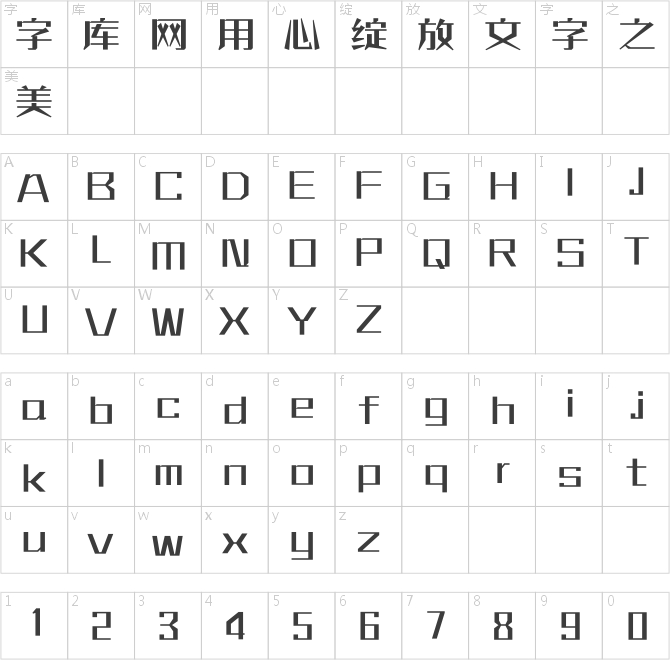
方正新恒刀刃體 詳情頁
方正新恒刀刃體字體下載
方正新恒刀刃體是在老式板報類字體的基礎(chǔ)上進行改良規(guī)范的,該字體所有筆畫全部以直線表現(xiàn),撇、捺、點、勾收尾處均采用切角處理,似刀頭、似利刃,故取名刀刃體,是一款既有力量感,又有活躍感,既有民國時期的風格,又具備新時代氣息的字體。適用于海報招貼、視頻媒體、產(chǎn)品包裝、書籍報刊及周邊領(lǐng)域。